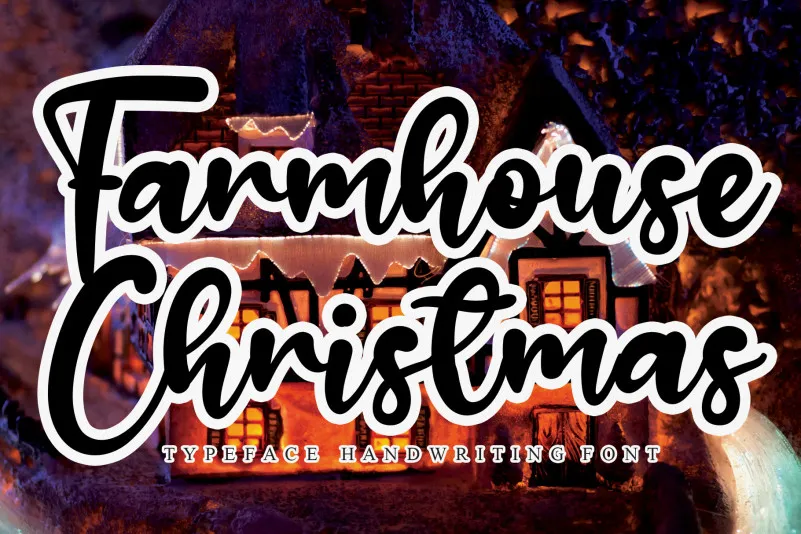
Farmhouse Christmas Script Font – Fonte Grátis
Farmhouse Christmas Script Font
A Farmhouse Christmas Script Font é uma delicada e elegante fonte escrita a mão que captura o espírito natalino rústico. Suas letras distintas e bem redondas criam um design único, tornando-a um trabalho de arte. Admire sua versatilidade impressionante e use-a para criar designs incríveis. Seja você designer ou aficionado por ilustração, essa fonte certamente encantará seus olhos com seu estilo único e rústico natalino. É perfeito para quem busca uma mão escrita que transmite tranquilidade e alegria de um dia para o outro.